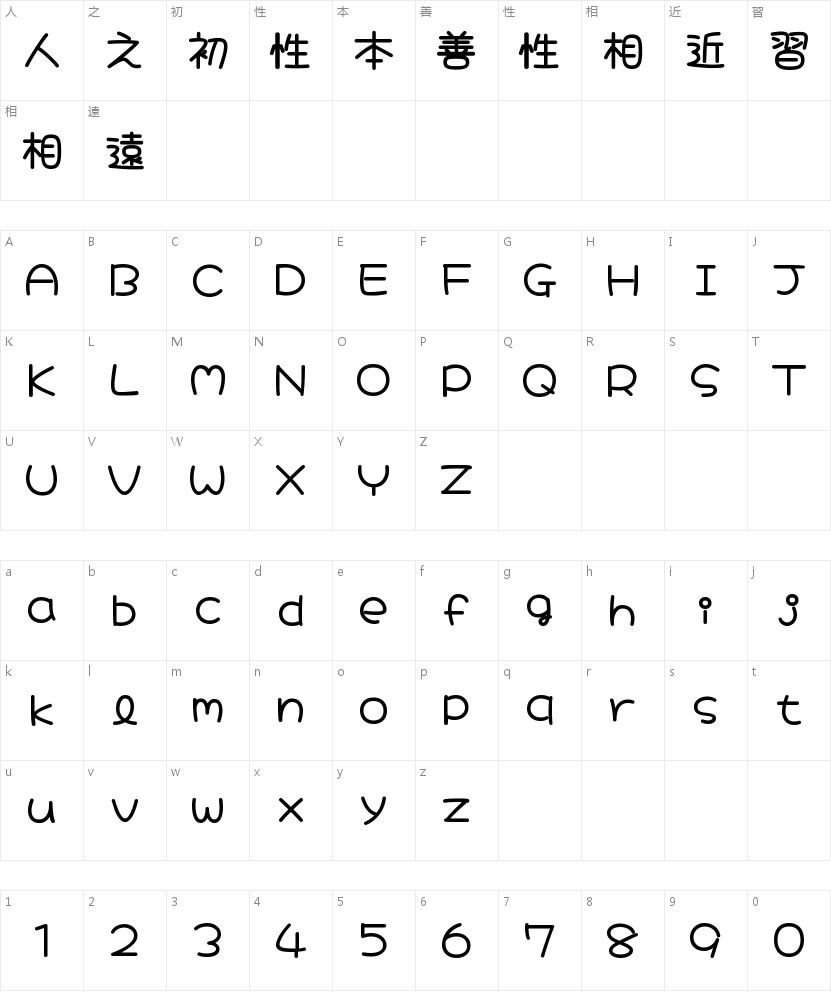
大波浪圆体-CJK-JP Bold
大波浪圆体-CJK-JP Bold是一种日文字体,具有加粗的特点,适合用于标题、强调文字等需要突出的地方。该字体的设计风格独特,字体笔画粗细均匀,线条柔和自然,使用该字体可以使文本看起来更加醒目、有力,同时也能为设计作品增添一份个性。 该字体可以在许多日文设计中使用,包括海报、广告、标识、书籍等。它的特点是粗体,使它在大型设计项目中非常突出和易于阅读,而且由于其设计风格独特,因此可以为设计添加一些独特的元素。
大波浪圆体-CJK-JP Bold是一款非常不错的手写艺术字体,具有很好的视觉感,适合于文化类的宣传设计、商业类品牌的广告和产品包装设计以及个性化文字排版等较多场景。